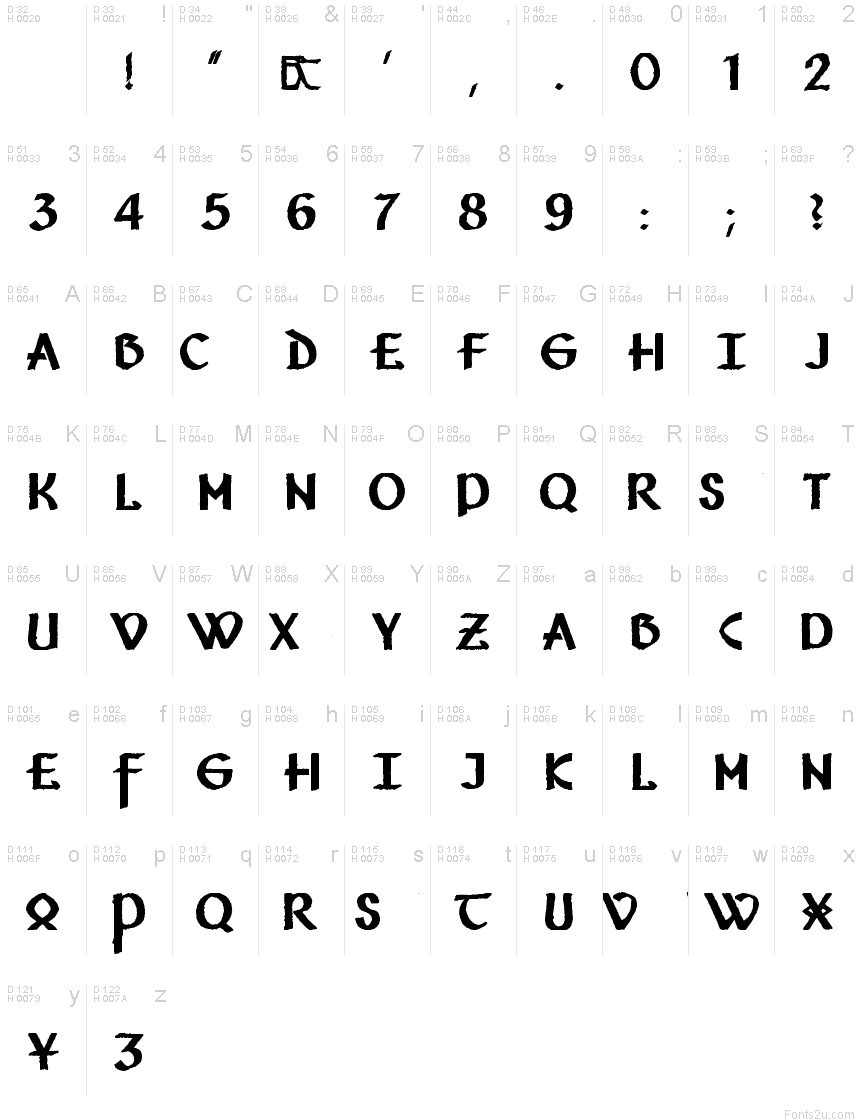
Vafthrudnir je bezplatné keltské gotické písmo, které dýchá atmosférou vytesaných legend a dávných severských rituálů. Písmena vypadají jako ručně opracovaná a jemně ošlehaná časem; mají masivní tahy, klínovité zakončení a pár runových záhybů, které dodávají textu drsnou, nikoli však dekorativní texturu.
Tento font zdarma se hodí pro projekty, které vyžadují mýtický nádech, historický kontext a kapku pohanské dramatičnosti. Obálky knih, herní tituly, vizuály kapel, nadpisy plakátů nebo festivalový branding si s jeho surovým, rituálním charakterem skvěle rozumí. Skvěle poslouží také pro krátké titulky, úvody kapitol či monogramy, kde nerovnoměrný, tesaný vzhled dodá i několika málo písmenům skutečnou osobitost.